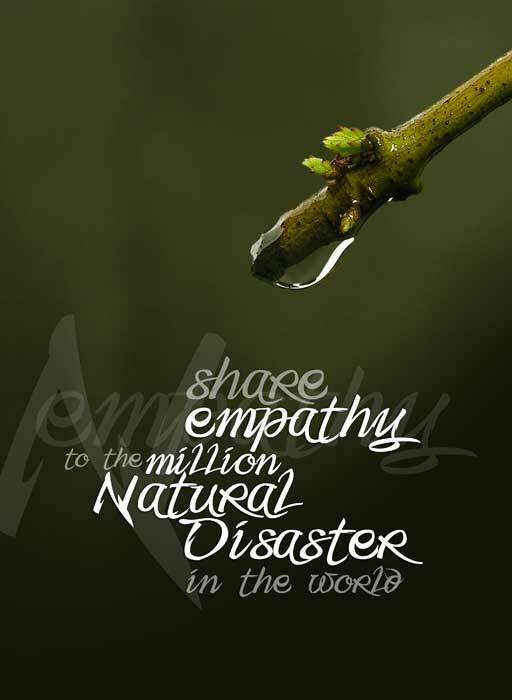
Fmiring Campotype One to darmowy, odręczny krój pisma typu brush autorstwa Andi Aw Masry, stworzony w 2008 roku z wyrazistym, modowym charakterem. Szerokie, "atramentowe" pociągnięcia łączą się z ostrymi zakończeniami i nagłymi zmianami tempa, co nadaje połączonym literom swobodny, autorski wygląd z efektownymi, kanciastymi momentami.
Ten darmowy font świetnie sprawdzi się w brandingu butików, na okładkach albumów, w edytorialach modowych, plakatach eventowych oraz opakowaniach perfum i kosmetyków. Szczególnie dobrze wygląda w krótkich nagłówkach i na planszach tytułowych, gdzie długie linie mają miejsce, by się rozciągnąć, a ostre akcenty nadają całości dramatyczny rytm.
F-Miring (po indonezyjsku „font pochylony”) to krój zainspirowany moim charakterem pisma i na nim wzorowany.